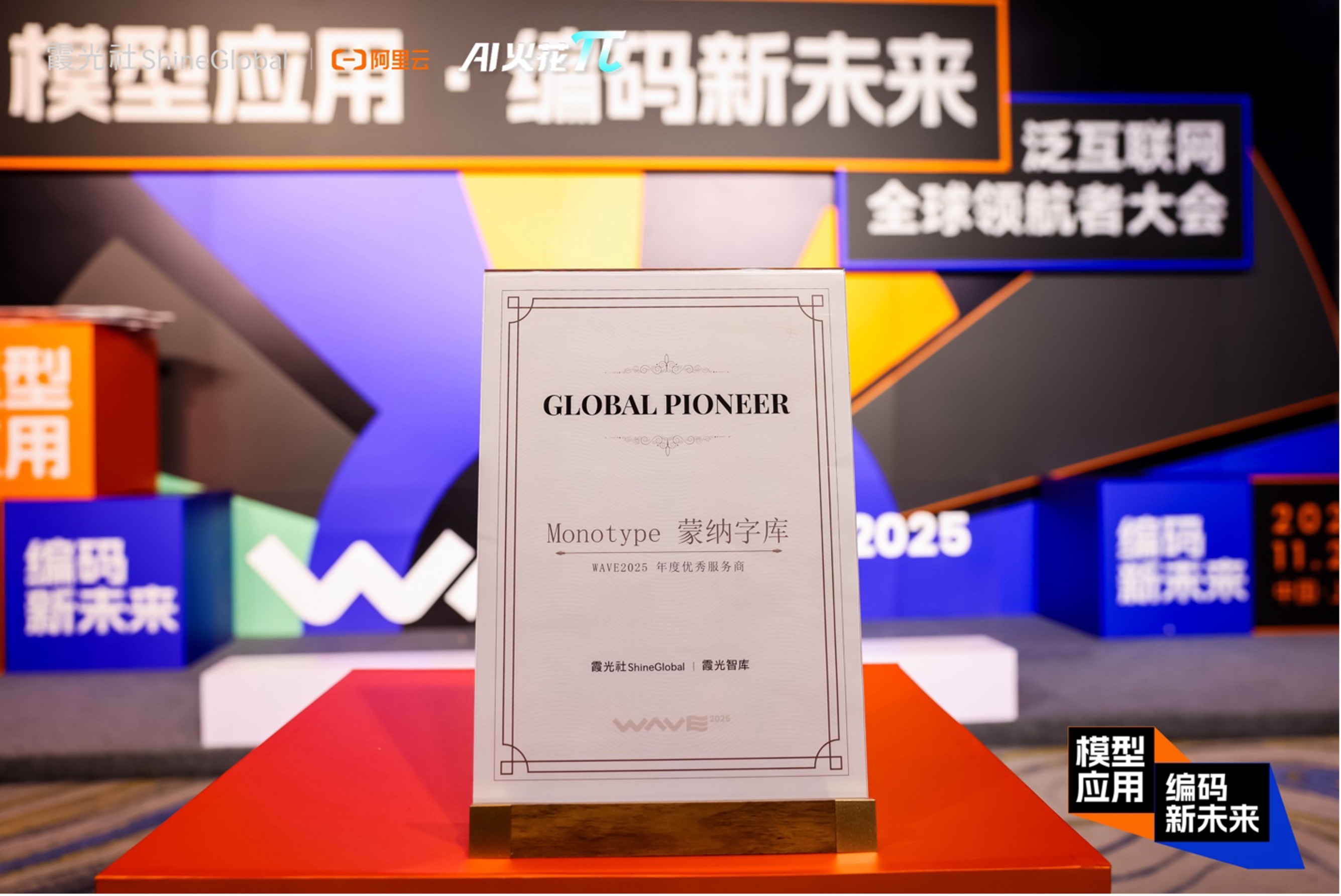
近日,由霞光社(ShineGlobal)与霞光智库联合第三方机构主办的 「WAVE 2025 泛互联网全球领航者年度榜单」 在上海揭晓。该榜单聚焦出海企业、投资机构与服务商,共评选出 50 家在全球舞台上以「中国品牌故事」重塑竞争格局的先锋力量。作为对长期主义与价值创造的致敬,榜单不仅是一份荣誉,更是一份面向未来的行业宣言。
蒙纳字库(Monotype)凭借其在字体技术与跨文化视觉表达领域的深厚积累,与阿里云等企业共同荣获「WAVE 2025年度优秀服务商」。该奖项是对蒙纳字库深度参与中国品牌出海进程、以字体技术搭建跨文化沟通桥梁所做贡献的高度认可。
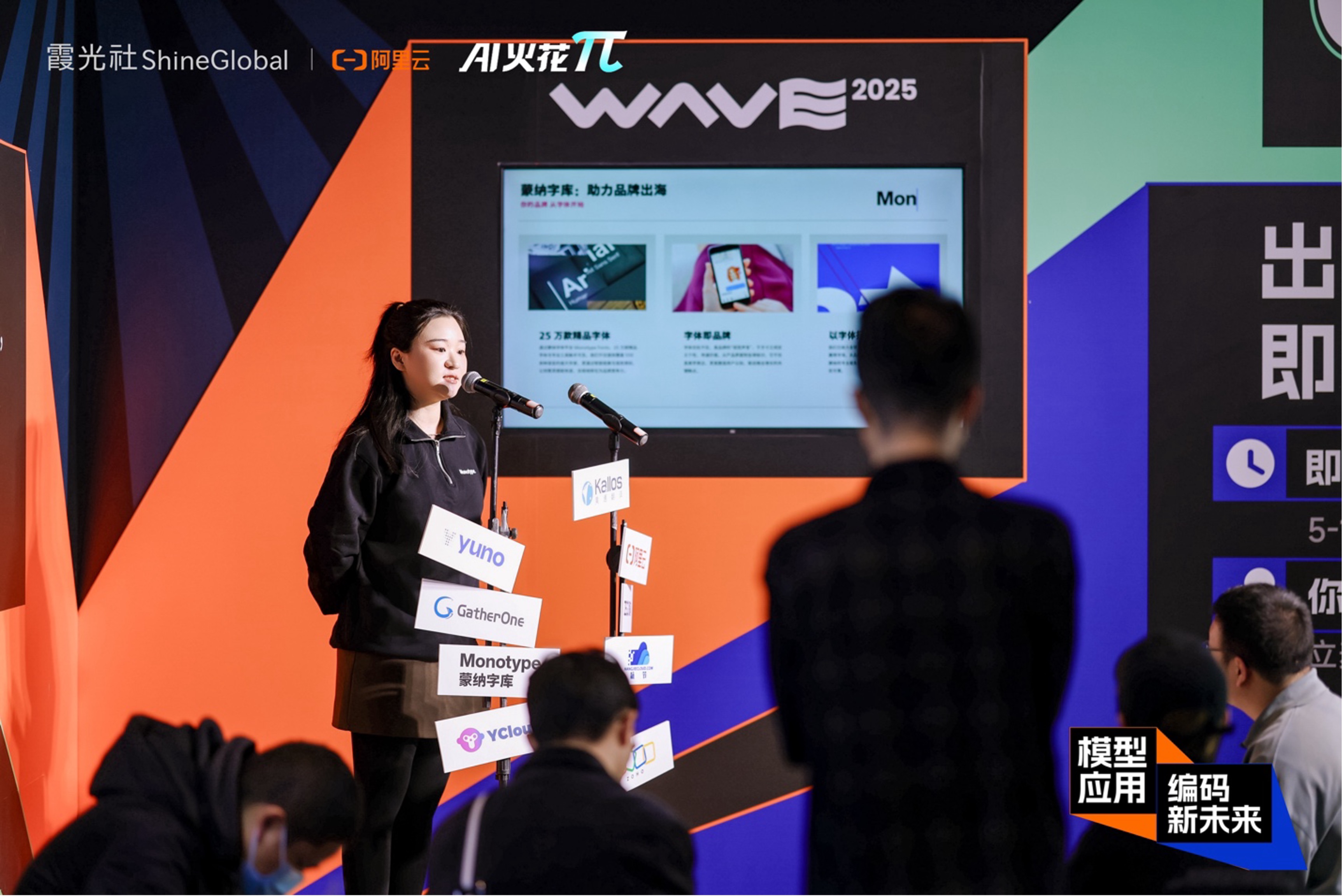
在大会特别设置的「出海轻讲台:即时发声计划」环节中,蒙纳字库代表 Sunny Xiang 向现场观众生动分享了蒙纳如何通过字体设计与技术解决方案,赋能中国品牌跨越文化边界、实现全球化视觉表达。她强调:“在全球市场,一个字体不仅是品牌识别的一部分,更是与当地用户建立情感连接的媒介。”
以字体为舟,助中国品牌扬帆全球
在全球化浪潮下,超 70 万中国企业已踏上或规划出海之路。而视觉表达的本土化与文化适配,成为品牌跨越地域边界的关键挑战。作为拥有百年历史的全球知名字库服务商,蒙纳正以其庞大的字体资源、先进的多语言技术与深度的文化洞察,成为中国品牌出海不可或缺的视觉伙伴。
全球资源:覆盖25万+字体,支持550+语言
Monotype Fonts 平台汇聚超过 25 万款字体,支持全球 550 余种语言,为品牌提供真正意义上的全球化排版解决方案。
智能技术:实现跨文化视觉统一
蒙纳推出的多语言智能字体配对功能,可自动推荐风格协调、视觉一致的多语种字体组合,覆盖中英日韩、阿拉伯文、俄文等复杂书写体系,确保品牌形象在全球范围内高度统一。
文化洞察:尊重传统,规避风险
字体不仅是设计元素,更是文化载体。蒙纳全球专家团队深谙各地排版习惯与文化敏感点,帮助品牌在拓展新市场时既保持调性,又避免文化误读。
成功实践:服务头部中国品牌出海
蒙纳已为阿里巴巴、腾讯、长城汽车等知名企业定制专属字体。其中,Alibaba Sans 助力其全球品牌表达;“腾讯字体”强化数字生态一致性;“长城黑体”则成为国内首款专为车载屏幕优化的屏显字体,彰显技术与场景的深度融合。
平台赋能:一站式字体管理,简化全球协作
Monotype Fonts 企业级管理平台支持从设计到部署的全流程管控,无缝对接主流设计工具,并提供网页嵌入、移动应用集成、服务器部署及多级权限管理,显著提升跨国团队的协作效率。
技术为桨,文化为帆
在泛互联网企业加速出海的时代,字体是品牌的无声代言人,更是跨文化对话的桥梁。蒙纳字库将持续以技术创新为基、以文化共鸣为桥、以用户联结为脉,助力更多中国品牌在全球舞台讲述属于自己的故事。